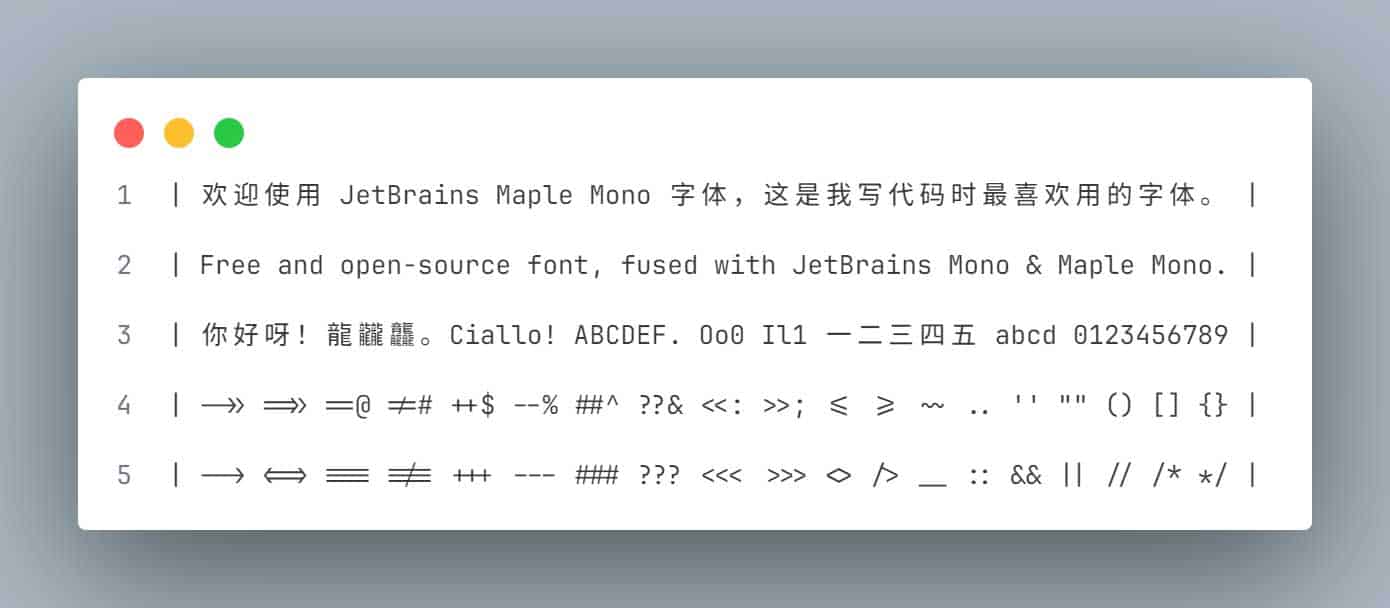
JetBrains Maple Mono:开发者理想的开源合成字体
JetBrains Maple Mono 是一款免费开源的合成字体,旨在通过融合 JetBrains Mono 与 Maple Mono 的各自优势,解决原生 JetBrains Mono 在中日文字形上的缺失问题。该字体采用无衬线设计,确保中英文字符严格遵循 2:1 的宽度比例精准对齐,在提供极高可读性的同时,原生支持智能连字、Nerd Font 及 Hints 渲染。
核心特性
• 精准对齐: 等宽无衬线设计,中英文 2:1 比例完美对齐,视觉排版整齐。
• 功能完备: 支持多种字重与智能连字,内置 Nerd Font 符号,原生支持 Hints。